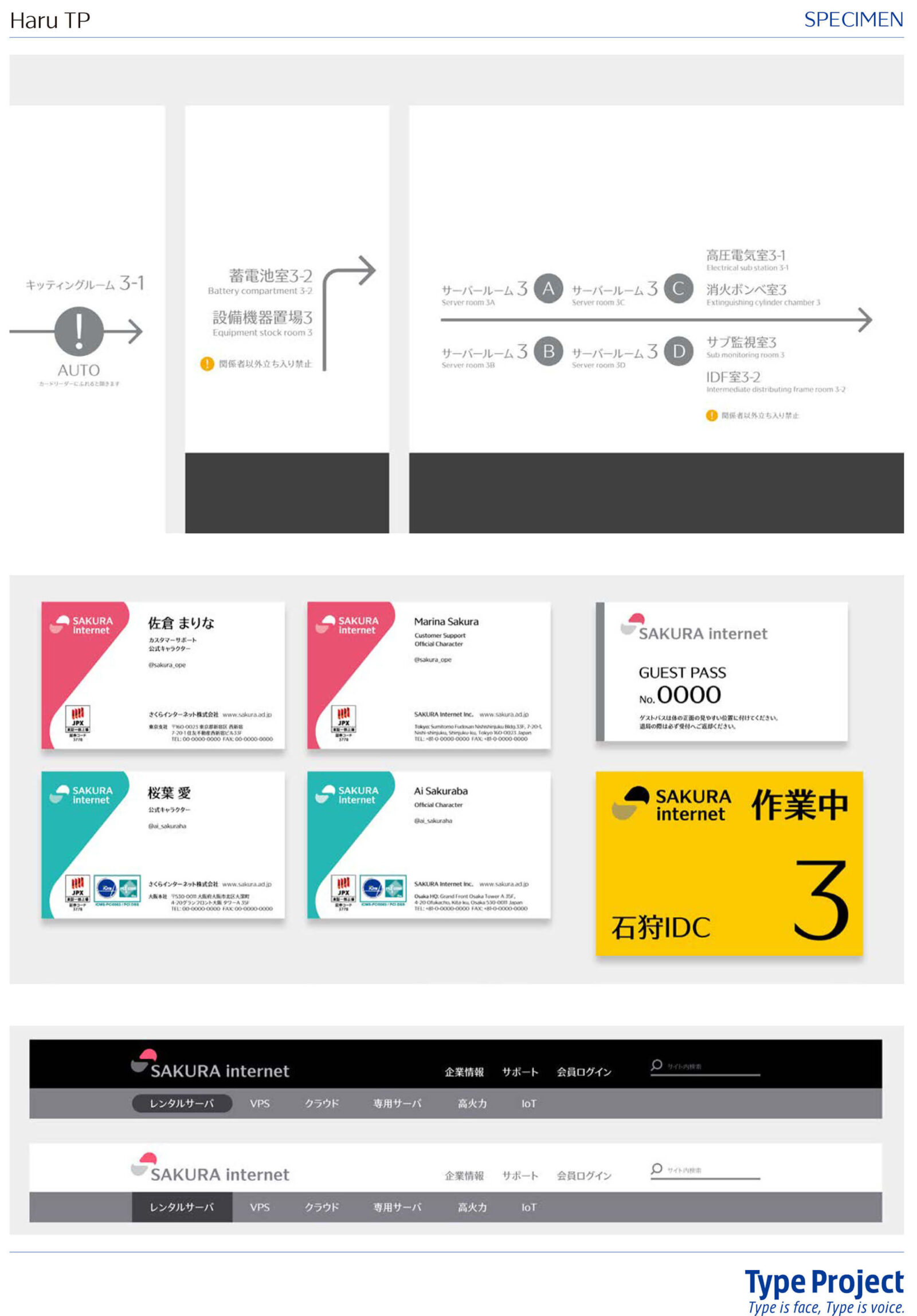
さくらインターネット、コーポレートフォントとして タイププロジェクトの「TP スカイ」のカスタマイズ版を導入
- 主要な欧文と数字を日本デザインセンターが制作 -
さくらインターネット株式会社(本社 大阪市北区 代表取締役社長 田中 邦裕 以下、さくらインターネット)と株式会社日本デザインセンター(本社 東京都中央区 代表取締役社長 原 研哉 以下、日本デザインセンター)、およびタイププロジェクト株式会社(本社 東京都練馬区 代表取締役社長 鈴木 功 以下、タイププロジェクト)は、さくらインターネットがタイププロジェクトの TP スカイのカスタマイズ版をコーポレートフォントとして導入したことを発表しました。さくらインターネットのコーポレートフォントとなる「Haru TP(はる てぃーぴー)」では、主要な欧文と数字を日本デザインセンターが制作しました。
さくらインターネットは、創業 20 周年を迎えるにあたりロゴを一新し、合わせてコーポレートフォントを新しく導入しました。ロゴデザインは日本デザインセンターが担当し、ロゴに合わせた欧文書体164字を作成しました。タイププロジェクトは、4月に発売を開始した新フォント TPスカイの欧文の一部を入れ替えるとともに、仮名7文字のデザインをさくらインターネットのロゴイメージに合わせて変更して提供しています。
さくらインターネットの技術本部 UX デザイングループ 河原覚は、「20周年を機にリブランディングを行うにあたり、ロゴを含む VI 全体の再構築を日本デザインセンター社にお願いしました。その中で、Webや紙媒体はもちろん、データセンターなど設備のサインまでもをひとつに繋げるものとしてご提案いただいたのが、フォントです。タイププロジェクト社の TPスカイをベースに欧文や仮名をカスタマイズし、弊社のイメージに合うフォントをご提案いただけたことをとても嬉しく思っています」と述べています。
TP スカイをベースとした Haru TP は、ライト、レギュラー、ミディアム、ボールドの4ウエイトで、名刺や社員証、カタログ、Web サイト、データセンターのサイン表示に使用されます。
「リブランディングに際しては初期の段階から、Web や印刷物を独自のフォントをもちいて、社員のみなさん自身が運用することを構想していました。日本のウェブの黎明期から活動されていたさくらインターネット社にふさわしい、自律的なブランディングの方法論に感じたからです。そうした願いを込めて、桜が咲く季節である『Haru』という名前を提案しました。Haru TP の欧文はサンセリフ書体を基本としながら、緩急のついた日本的なシルエットを目指しています。このプロジェクトを、タイププロジェクトを含めた3社の共同で進められたことを、とても幸運に、そして光栄に思います」と、ロゴおよび欧文書体のデザインを担当した日本デザインセンターのオンスクリーン・デザイン研究所 アートディレクター 有馬トモユキは述べています。
タイププロジェクトでは、企業のメッセージを伝えるための手段としてフォントによるブランディングを提案しています。フィットフォント技術を用いて、既存フォントのウエイトやコントラストを調整したり、他社欧文と組み替えるほか、オリジナルのひらがなやカタカナを開発するなど、世界有数のグローバル企業にコーポレートフォントを提供しています。
タイププロジェクトの鈴木功は次のように述べています。「フィットフォントを基盤としたカスタマイズフォントを提供することは、タイププロジェクトの得意とするところです。今回は、発売したばかりの TPスカイをカスタマイズしてコーポレートフォントとして提供できたことをたいへん光栄に思っています。さくらインターネット社の『声』とも言える Haru TP は、企業イメージに一貫性を与え、信頼性という資産の形成に役立つ事を確信しています」